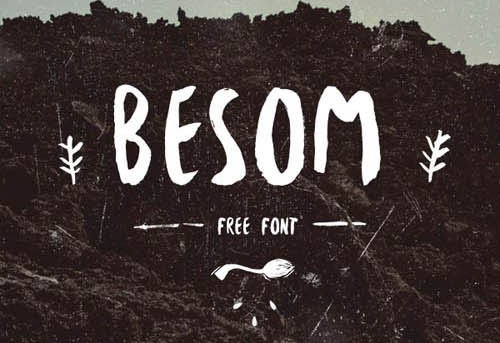
Besom Handwritten Brush Font – Download Grátis
A fonte Besom Handwritten Brush Font é uma escolha ideal para qualquer projeto que busque uma atmosfera envolvente e natural. Ela foi criada pelo designer Hamilton, resultando num estilo de escrita bem suave e delicado, perfeito para aplicar em designs onde deseja-se transmitir a sensação de conforto e paz. Esta fonte Brush é especialmente adequada para uso em cartões de aniversário ou outros materiais promocionais que buscam uma aparência natural, sem perder o toque elegante. Além disso, seu acabamento delicado e estilo cuidadosamente elaborado proporciona um brilho a qualquer projeto gráfico. Para os desenvolvedores de software ou designers que pretendem usar esta fonte para fins comerciais, é importante saber que Hamilton fez questão de manter o Besom Handwritten Brush Font disponível gratuitamente para esse tipo de uso. Ainda assim, vale ressaltar algumas orientações básicas sobre seu uso: não crie ilustrações digitais com base nela sem permissão prévia do designer. A fonte Besom Handwritten Brush é uma excelente adição ao seu portfólio de recursos gráficos, adequada para designs que buscam um toque pessoal e natural.